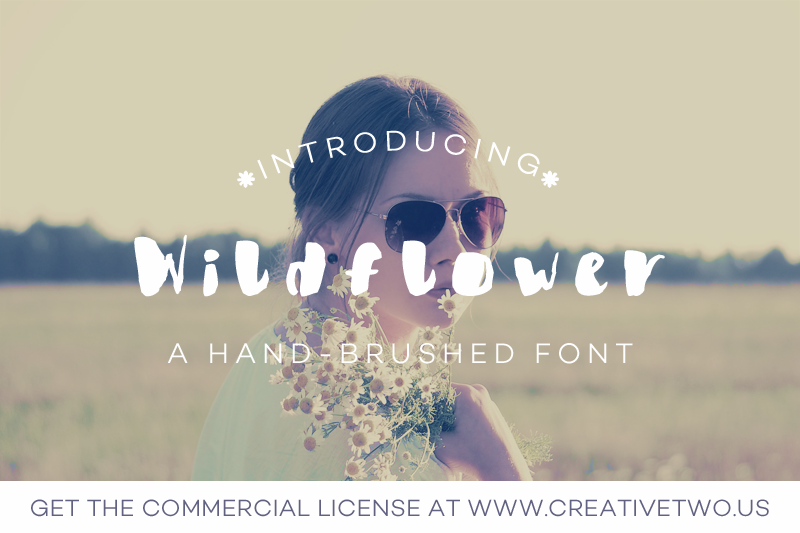
Wildflower Font – Download Grátis
A “Wildflower Font” é uma elegante seleção do gênero Brush Fonts, criada pelo designer Hamilton para quem adora a sensação naturalista que as plantas oferecem. Com seus traços grossos e desenhados à mão, essa fonte abrange letras maiúsculas e minúsculas, números e sinais de pontuação, trazendo a rusticidade em cada detalhe. Ideal para quem procura uma fonte que transmita um toque naturalista e amigável, especialmente no design gráfico pessoal. O uso comercial dessa font está disponível através do site especializado em fonts, www.fonts.creativetwo.us. Sem dúvidas é a escolha perfeita para aqueles apaixonados por plantas e pela natureza, trazendo um toque único e autêntico aos seus projetos.